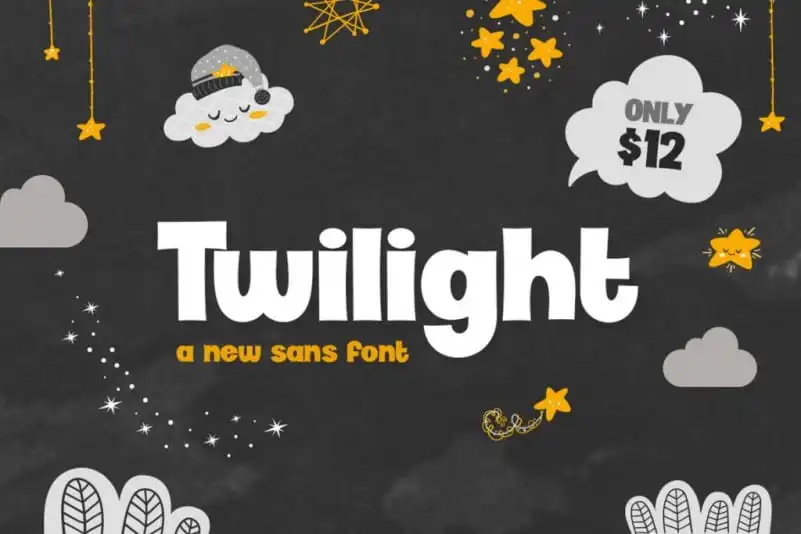
Olá! Estou aqui uma nova fonte de tipo sans-serif chamada Twilight Typeface. Introduzida pelo designer f0rdesigner, essa é uma excelente adição para qualquer projeto desejoso de estilo moderno e sofisticado. Twilight foi projetada por Salt & Pepper Designs e já está pronta para uso. Uma das características mais intrigantes desta fonte é a sua natureza clássica, mas ao mesmo tempo inovadora. O designer criou caracteres que oferecem uma reviravolta moderna sobre o tipo de sans-serif padrão, tornando-o único e perfeito para diversas aplicações. Este novo lançamento seria particularmente adequado para Instagram Quotes, logotipos e linhas de marca – certamente você não deve esquecer de combiná-lo com outras fontes serifadas modernas. Uma boa escolha se estiver buscando aperfeiçoar o seu projeto visual. Sem dúvida, a Twilight Typeface é uma adição indispensável para qualquer designer que procura uma nova opção de tipo em sua coleção.